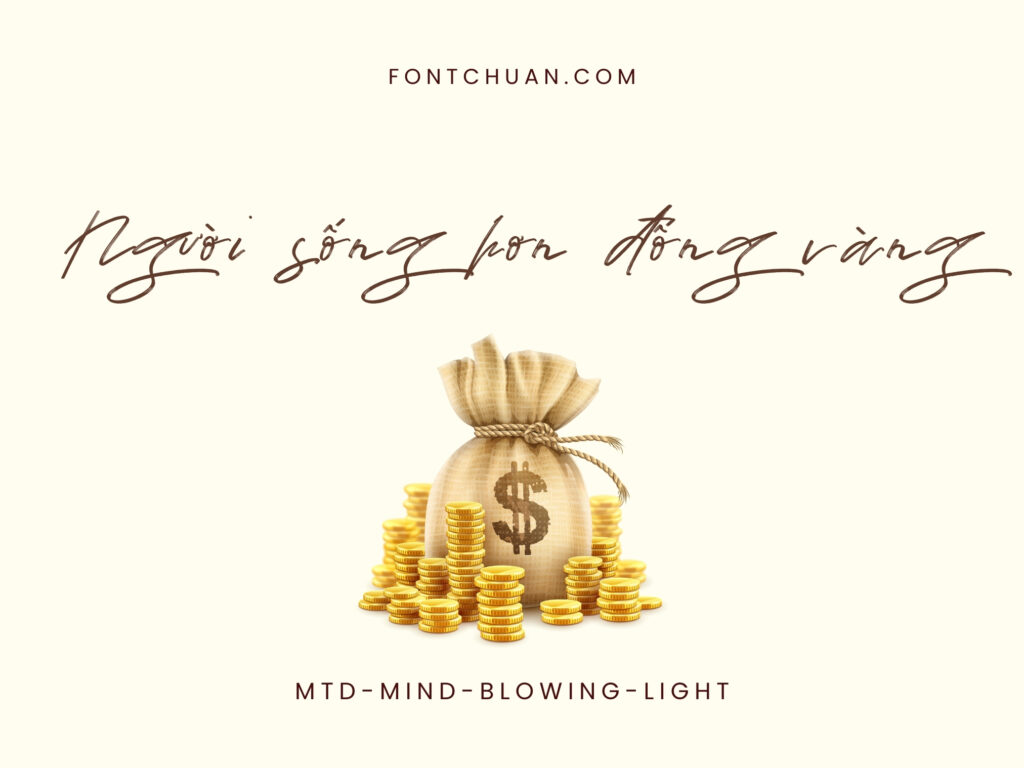
Font MTD Mind Blowing Light Việt Hóa
Font MTD Mind Blowing Light là một phông chữ script viết tay thanh lịch, nổi bật với các đường nét mềm mại và uyển chuyển, tạo nên cảm giác nhẹ nhàng và duyên dáng. Font đã được Việt hóa bởi Mộc Hạ, hỗ trợ đầy đủ tiếng Việt cùng hơn 90 ngôn ngữ khác, mở rộng khả năng ứng dụng trong nhiều lĩnh vực thiết kế. Đây là một trong những lựa chọn được cộng đồng sáng tạo đánh giá cao, đặc biệt khi cần truyền tải sự tinh tế và cảm xúc nhẹ nhàng trong từng dự án. Thành viên của Font Chuẩn đã chọn lọc, ứng dụng thực tế font này trong nhiều thiết kế thương hiệu, bao bì và thiệp mời, mang đến hiệu quả thẩm mỹ cao.
Với phong cách viết tay tự nhiên kết hợp cùng độ mảnh hài hòa, MTD Mind Blowing Light phù hợp cho các thiết kế tiêu đề, thiệp cưới, chữ ký, poster nghệ thuật và ấn phẩm truyền thông cần yếu tố cá nhân hóa. Các đường cong mượt mà và khoảng cách chữ hợp lý giúp font giữ được sự dễ đọc ngay cả ở kích thước nhỏ. Đây là font lý tưởng dành cho các ngành quảng cáo, công nghệ, giáo dục, thiệp cưới, ảnh cưới; và rất phù hợp sử dụng trong các dịp lễ hội như Tết, Giáng sinh, Valentine hay các sự kiện mang tính cảm xúc cao.